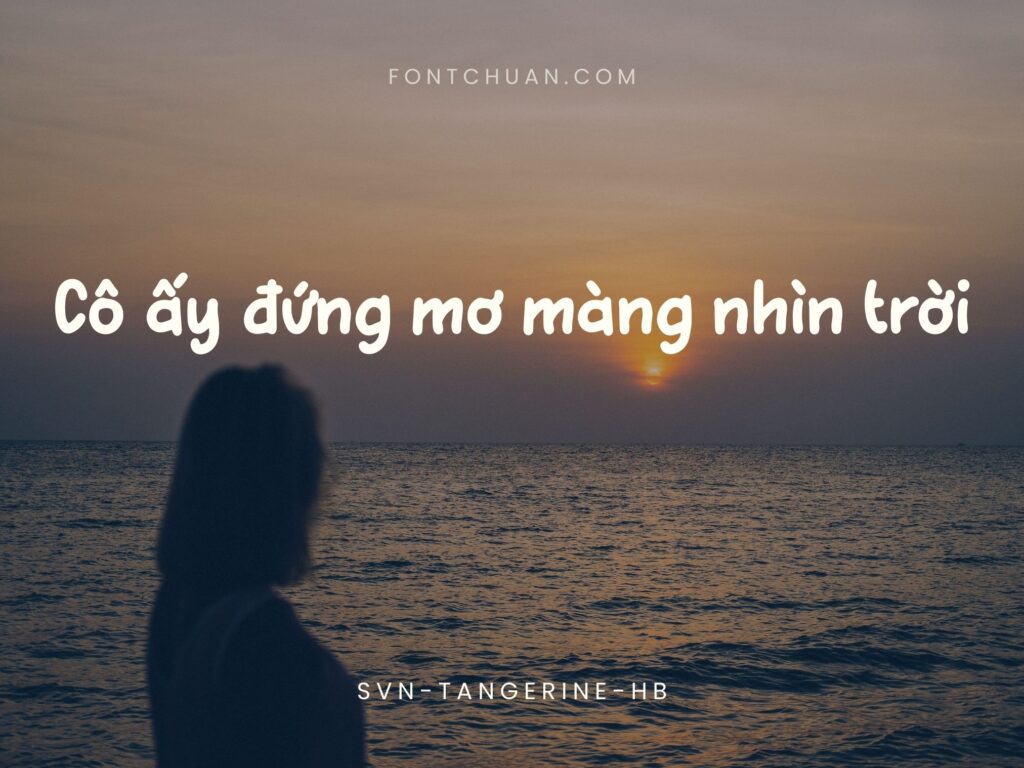
Font SVN Tangerine Hb Việt Hóa
Font SVN Tangerine HB là phiên bản Việt hóa của kiểu chữ Tangerine, được thực hiện bởi STYLEno.1 Fonts. Tangerine là một kiểu chữ viết tay dễ thương và đơn giản, phù hợp cho các trích dẫn trên bảng đen hoặc tài liệu giảng dạy. Font này mang đến cảm giác chân thực và cá nhân hóa cho các thiết kế của bạn.
SVN Tangerine HB lý tưởng cho các dự án thiết kế yêu cầu sự thân thiện và gần gũi, như thiệp mời, tiêu đề, logo và các ấn phẩm truyền thông. Các ngành nghề như giáo dục, ẩm thực và spa có thể tận dụng font này để tạo điểm nhấn trong thiết kế. Ngoài ra, font cũng thích hợp cho các sự kiện như Tết, Sinh nhật, Trung thu và các lễ hội khác.